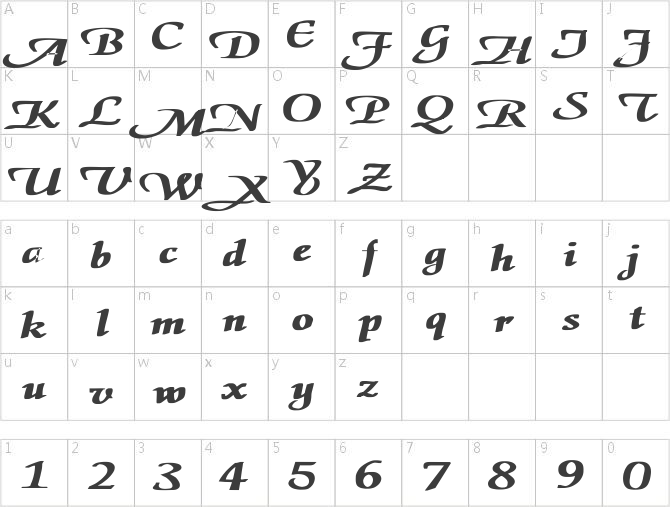
ElGar-Ex-Bold 詳情頁(yè)
ElGar-Ex-Bold字體字庫(kù)是一款讓人賞心悅目、百看不厭的英文字體,適合各類(lèi)廣告和產(chǎn)品包裝設(shè)計(jì)應(yīng)用,字體大小0.12MB,格式為ttf字體,上傳用戶(hù)是舒甜咖啡,作者/版權(quán)方為未知